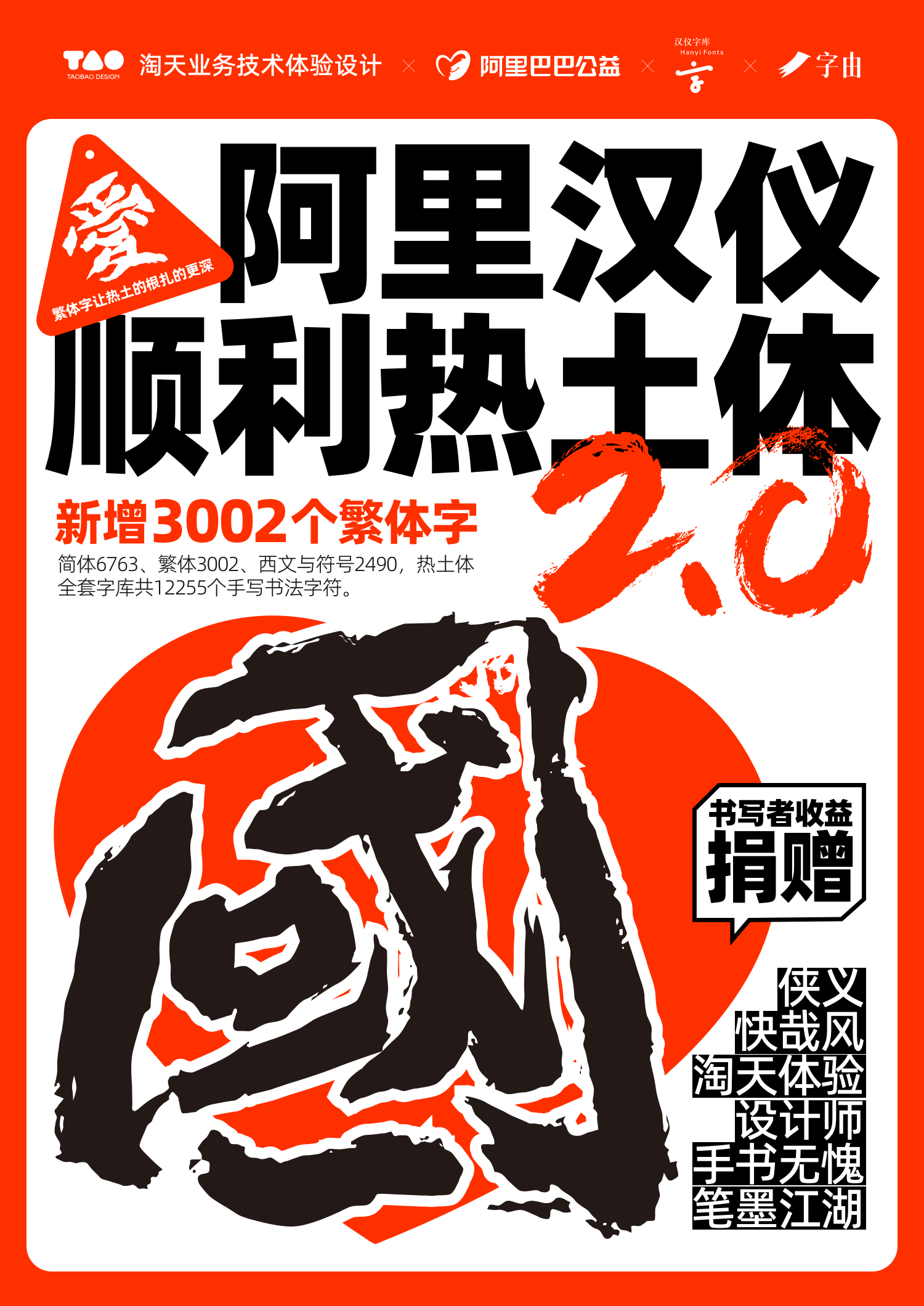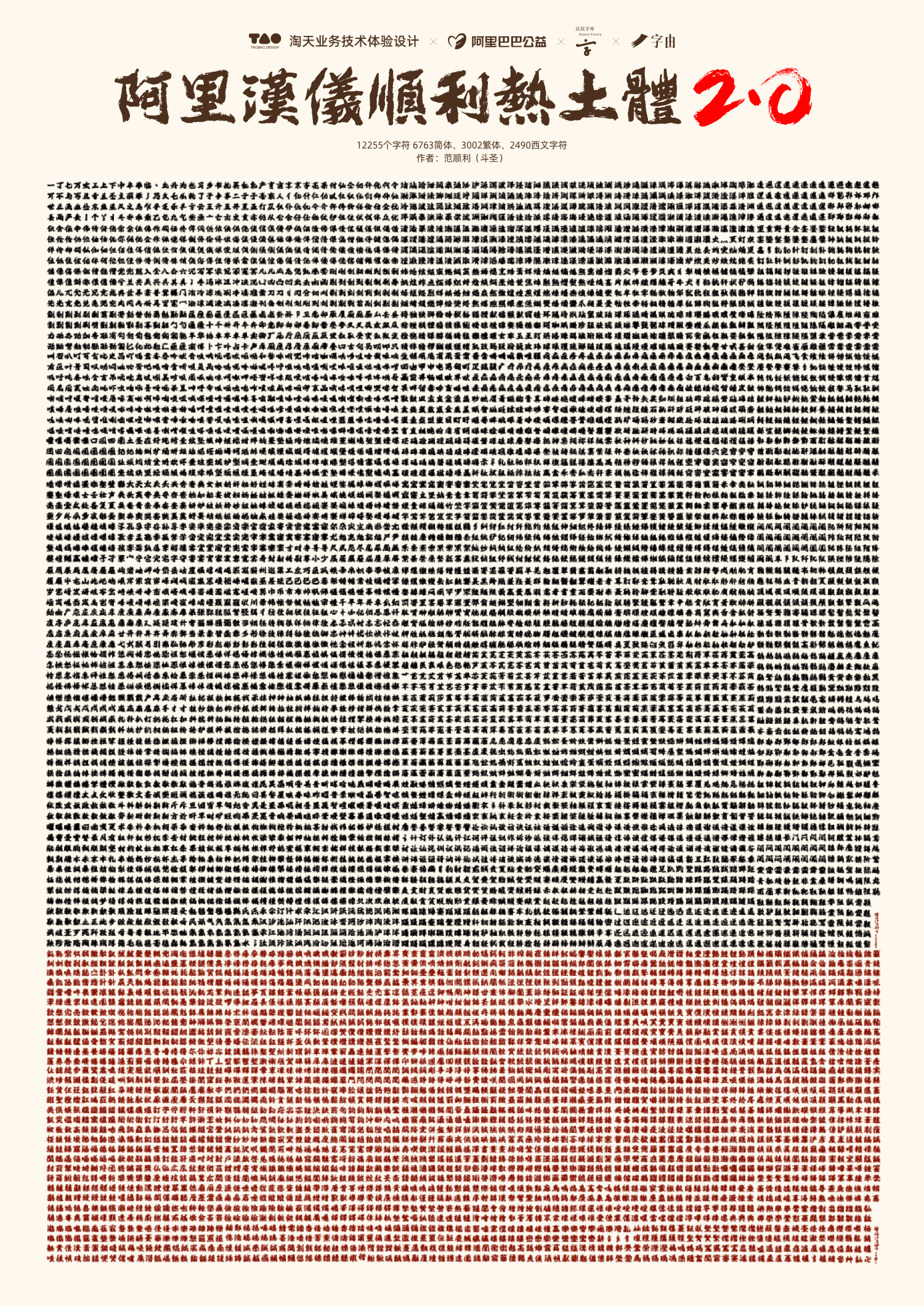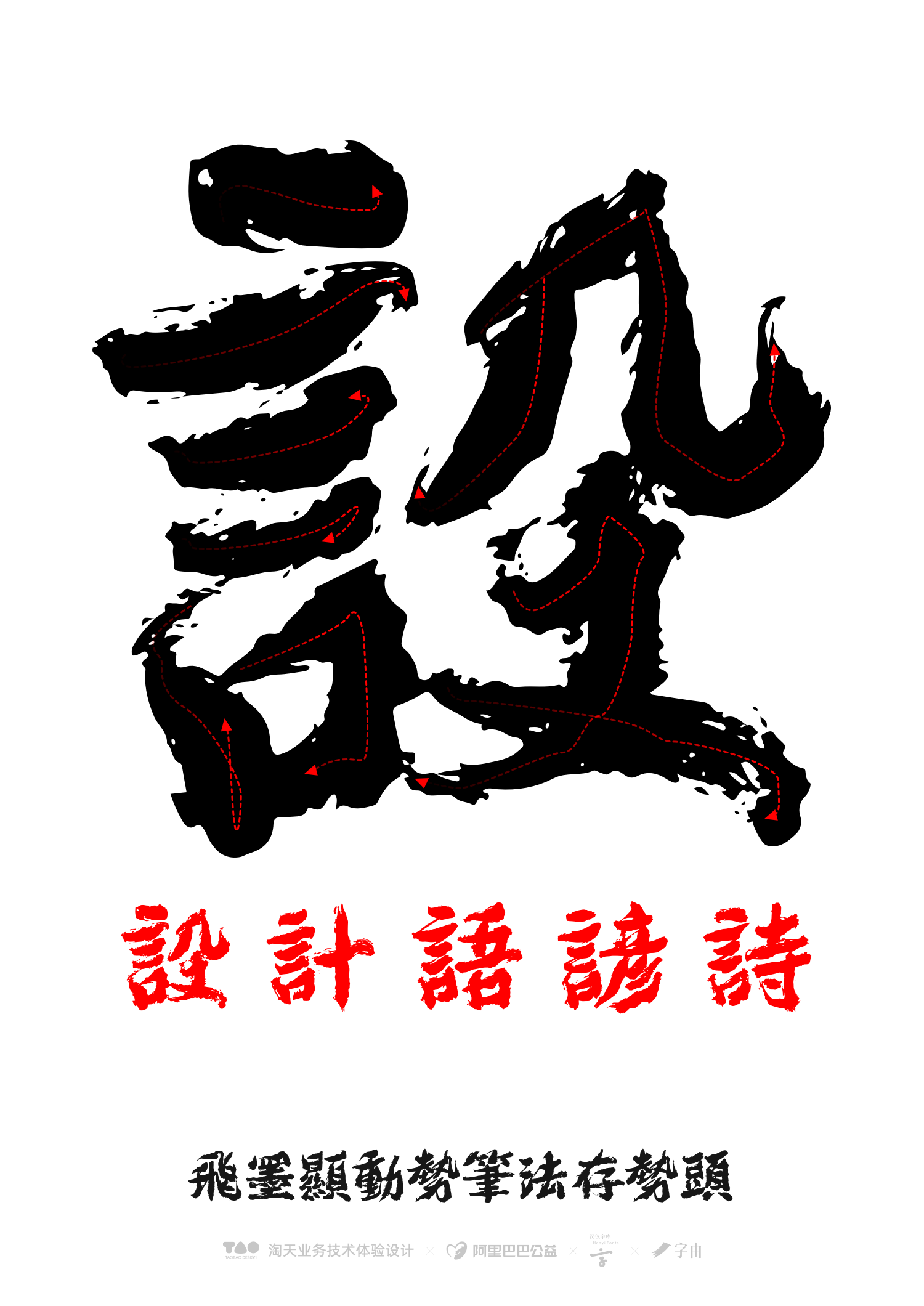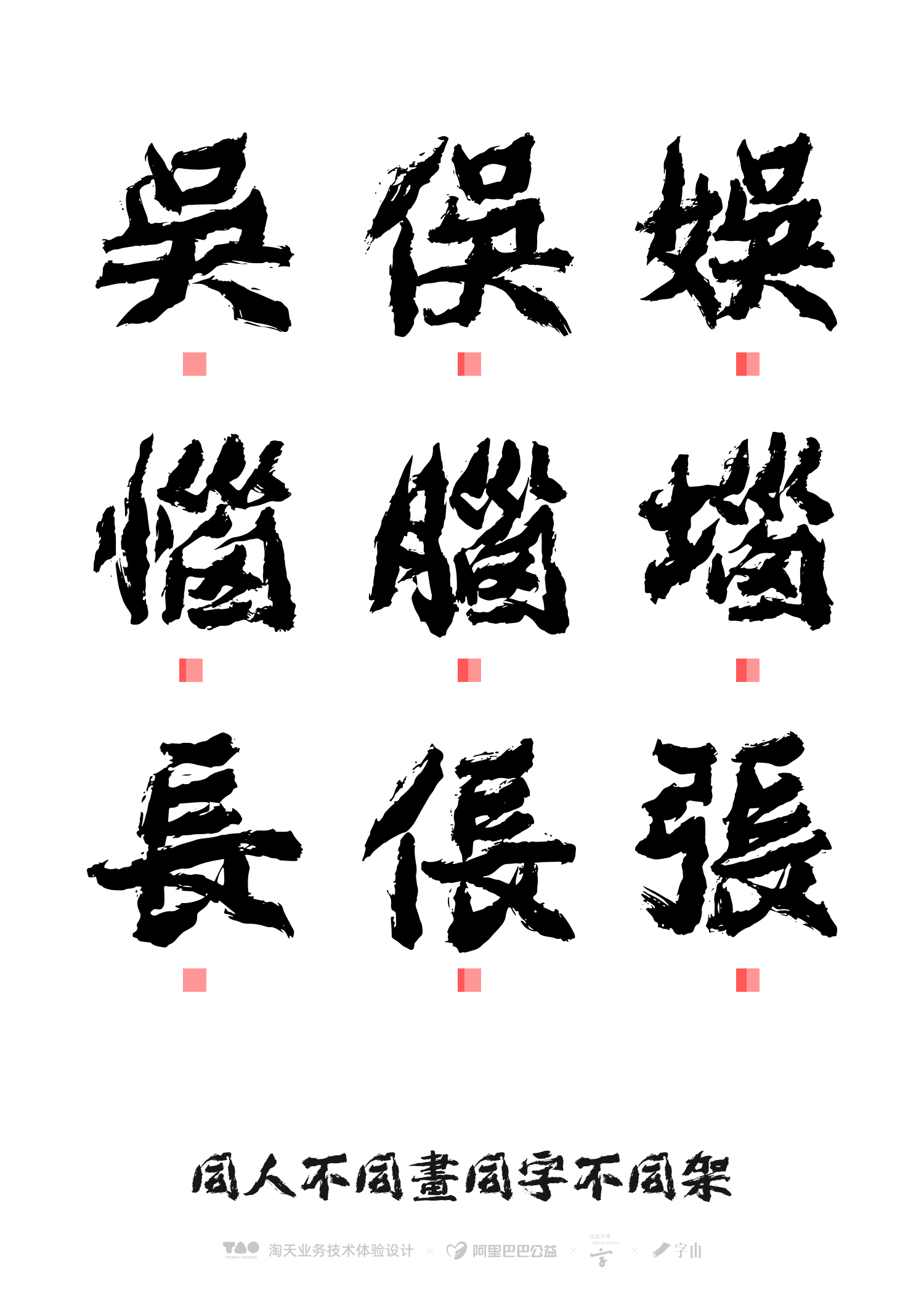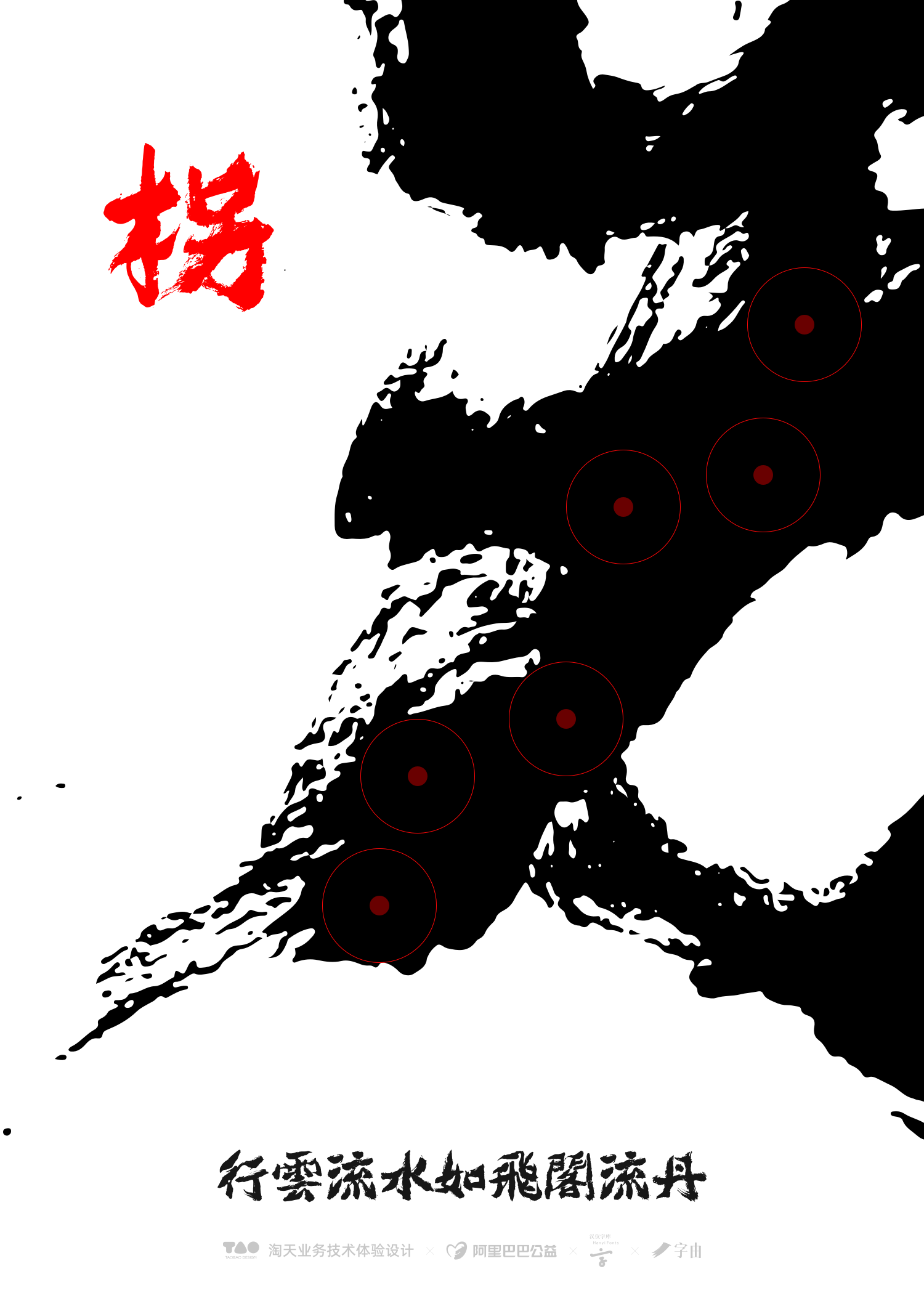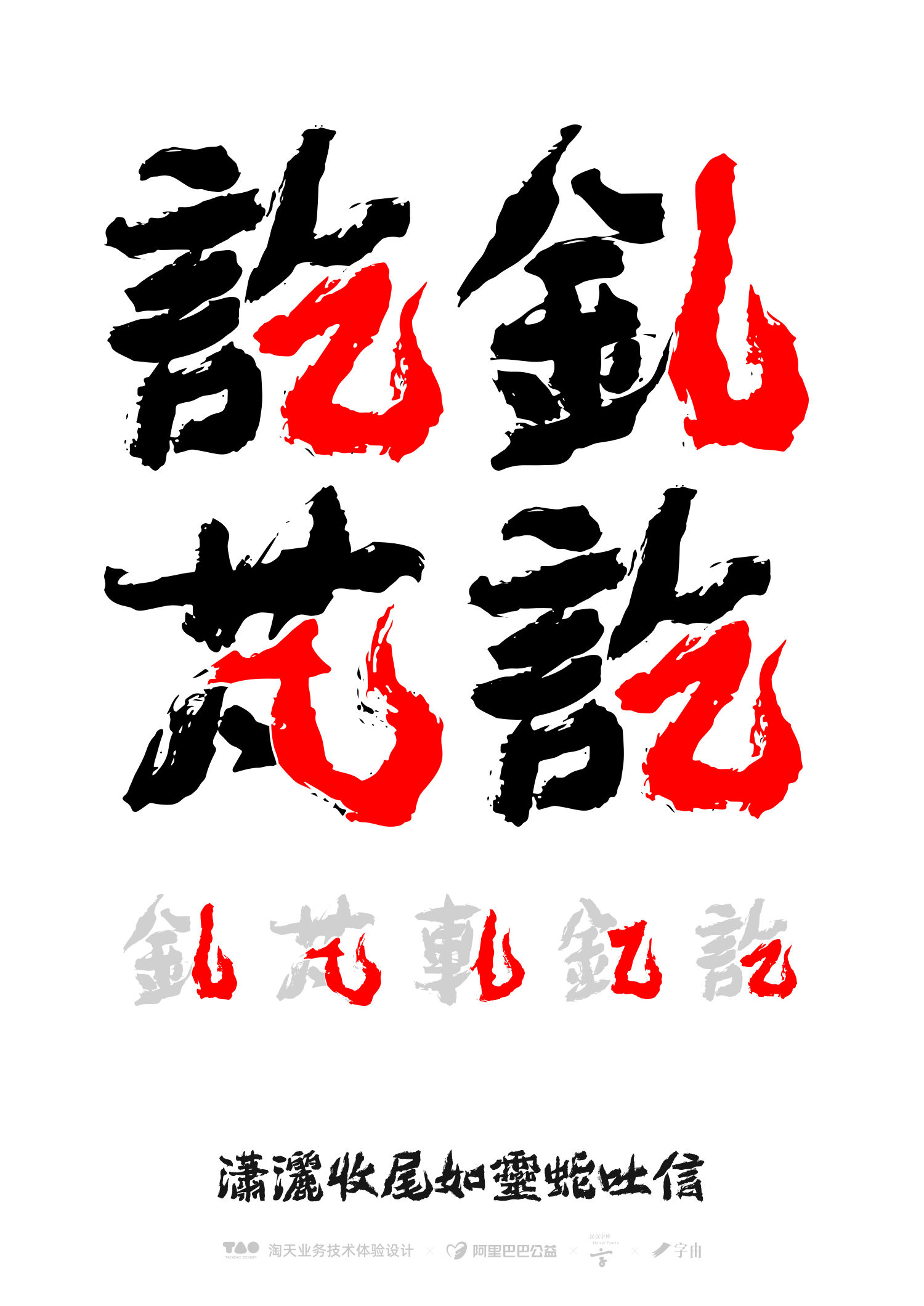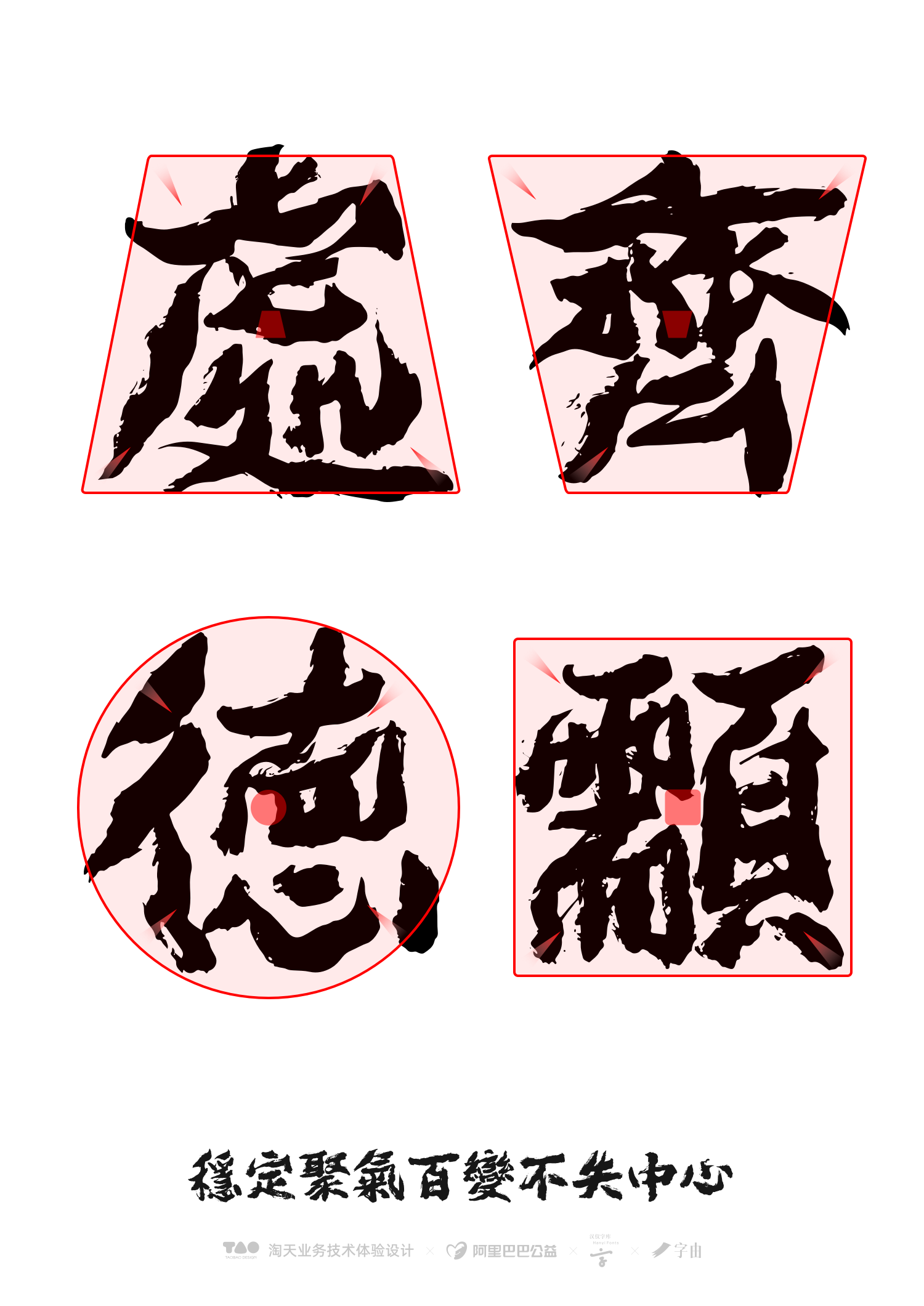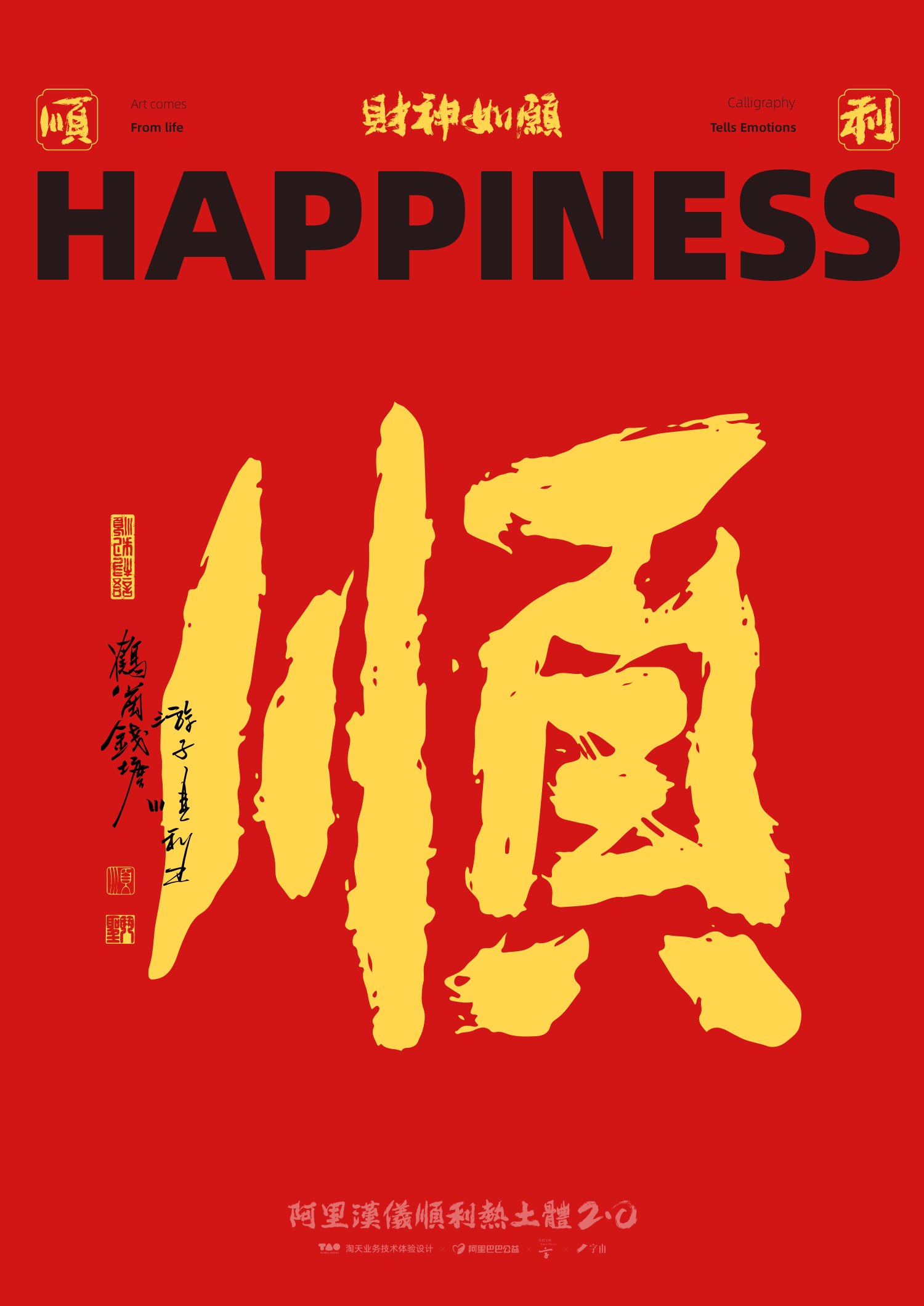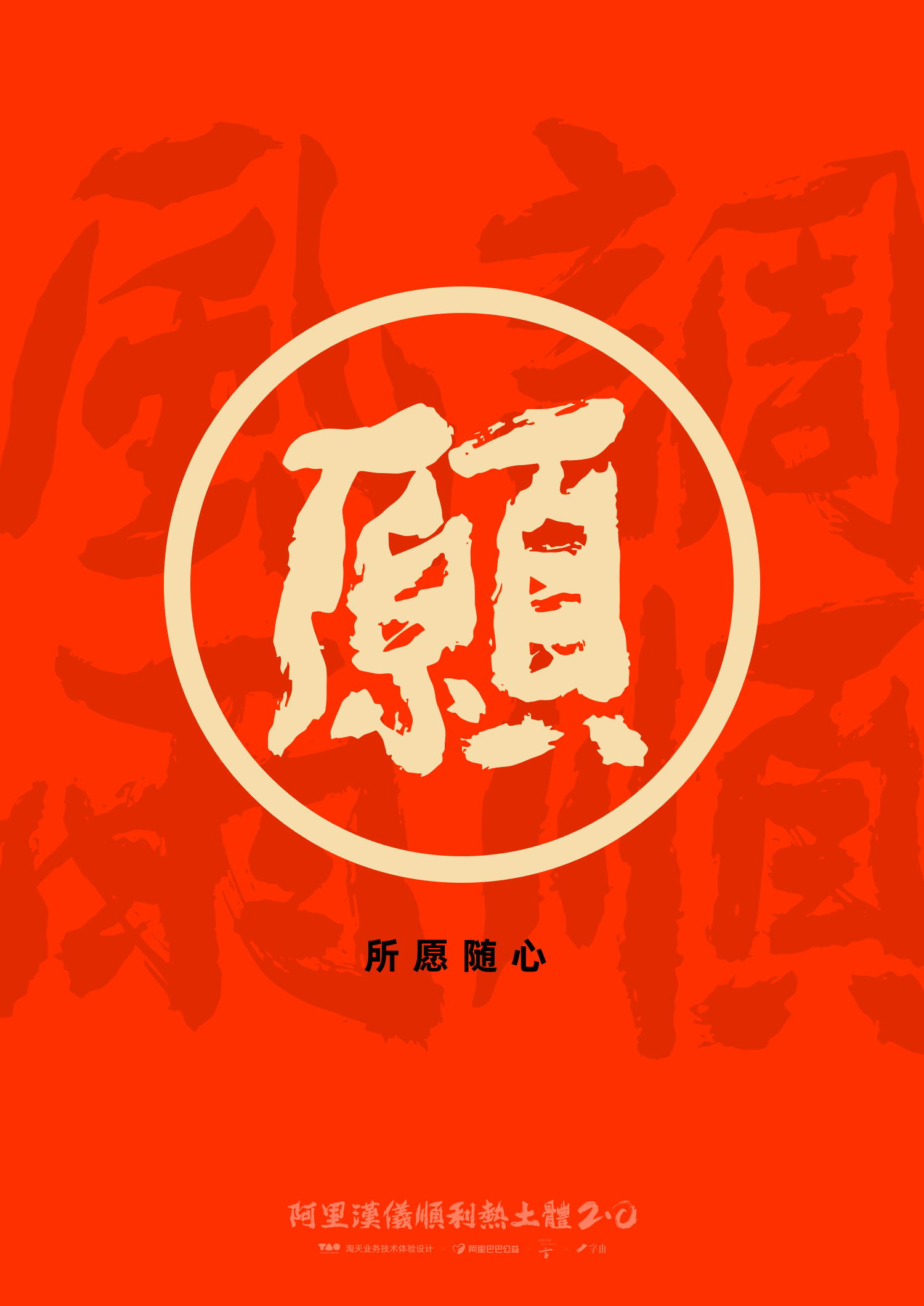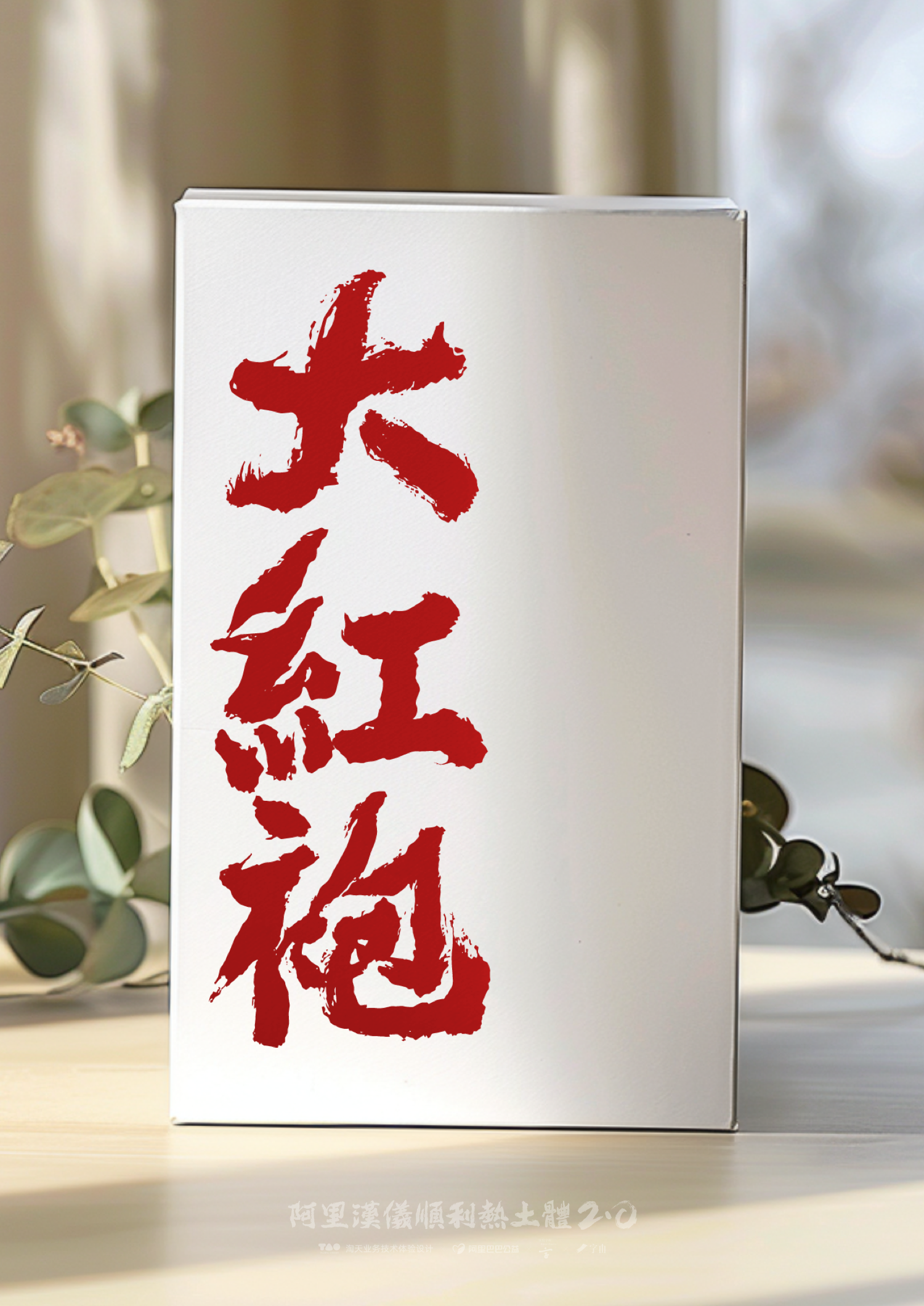
时近新春佳节,阿里汉仪顺利热土体V2.0繁体字符集终于制作完成!V2.0的字符集包含简体中文和繁体中文,将在字由平台进行独家公益售卖。
繁体中文共计3002字符,秉承了简体字符集的笔画风格,饱满酣畅的墨感与灵动的飞白交织,繁体字笔画更丰富,书写上更显精气神。
这是一款为我国欠发达地区的乡村用户打造的公益字体,更是传达热烈赤子心与国风书法之美的设计师必备节庆字体。
新春送福,灵蛇献瑞。我们还用阿里汉仪顺利热土体,穿插蛇年元素,设计了年味满满的新春福筒。